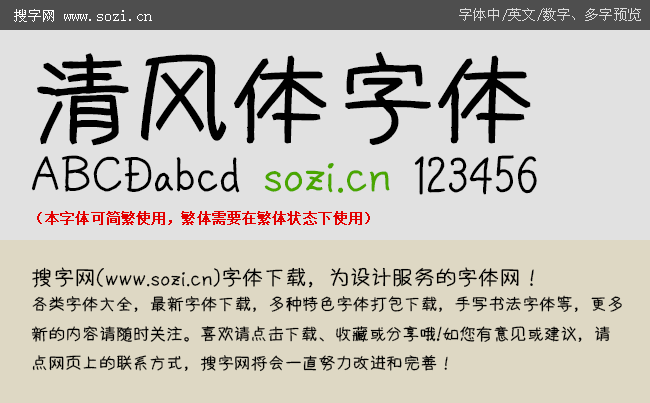
清風(fēng)體字體
搜字網(wǎng)給大家提供一款卡通手寫風(fēng)格的手機(jī)中文字體下載。名字叫清風(fēng)體字體,這款手機(jī)字體是仿照兒童手寫風(fēng)格的卡通手寫字體,結(jié)構(gòu)帶有POP字體風(fēng)格,特別適合喜歡手機(jī)字體個性一些的朋友在手機(jī)上安裝使用。